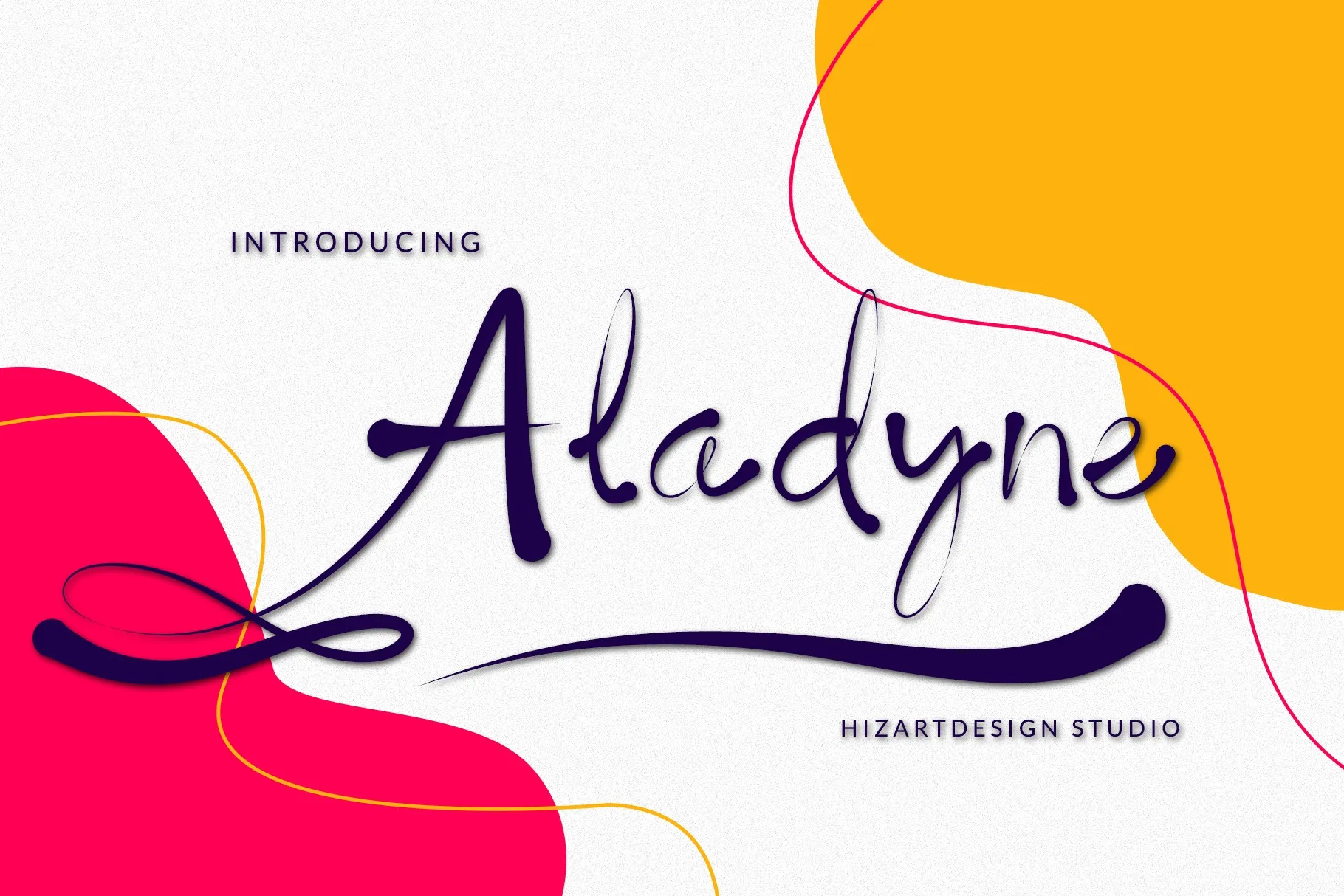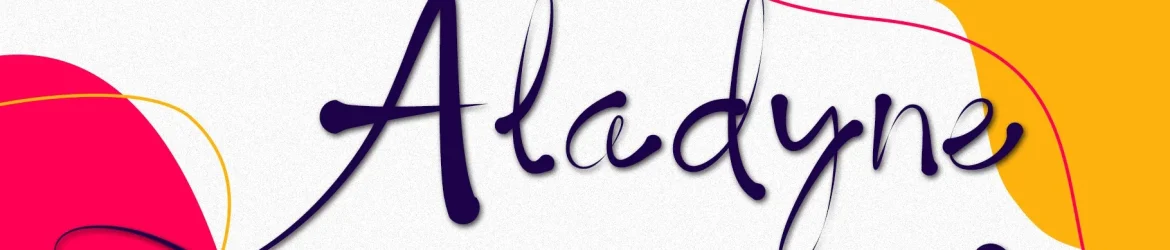
Aladyne Font – Download Grátis
A Aladyne é uma fonte moderna e elegante criada pelo designer Mahrizal Ramadhan com um fluxo natural e sofisticado. Ela traz designs encantadores que darão aos seus projetos um ar único e delicado, ao mesmo tempo em que apresentam caracteres elaborados e de alta qualidade. Ideal para uso em logotipos, cartões de agradecimento, design de embalagens, identidade da marca, criação DIY, títulos de livros, convites de casamento, embalagens e muito mais. Sua beleza moderna e elegância a tornam um recurso perfeito para qualquer projeto gráfico que deseje dar um toque único e refinado aos seus designs.